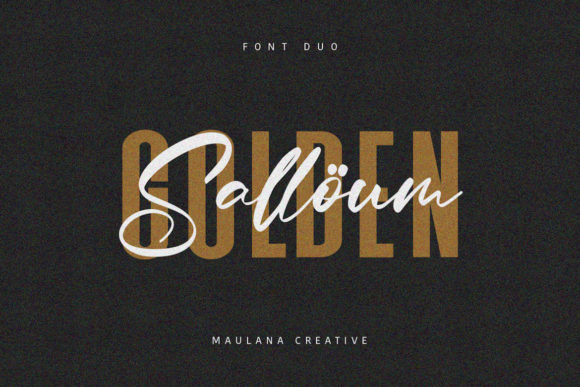
Salloum Golden Font Duo
قد يكون العثور على عناصر التصميم المناسبة أمرًا صعبًا، ولكن Salloum Golden Font Duo يقدم مجموعة استثنائية ترتقي بعملك على الفور.
سواء كنت تقوم بإنشاء منتجات الطباعة عند الطلب أو دعوات الزفاف أو رسومات وسائل التواصل الاجتماعي، فإن Salloum Golden Font Duo هو الخيار المثالي.